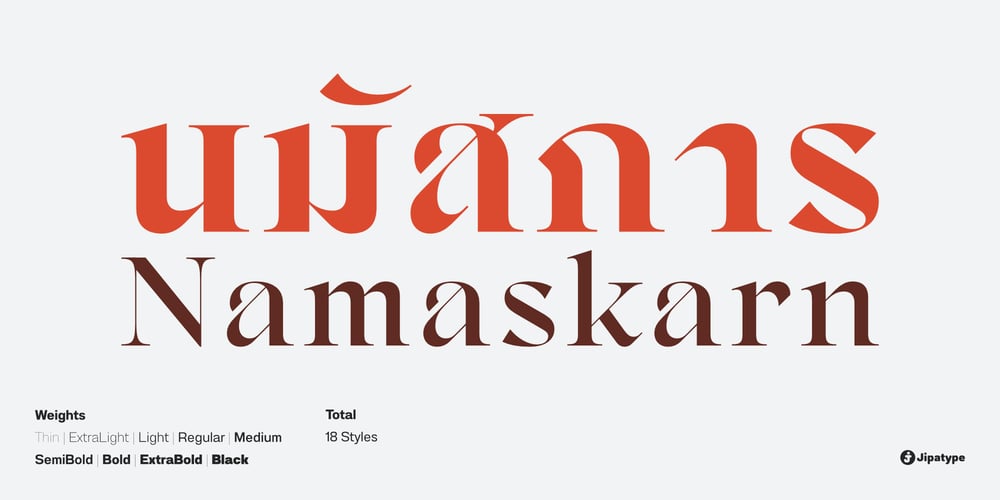
Namaskarn Font Family was designed by Anupap Jaichumnan and published by Jipatype. Namaskarn contains 18 styles and family package options. ฟอนต์ นมัสการ แบบอักษรได้แรงบันดาลใจจากเขียนตัวอักษรวิจิตรด้วยปากกาหัวตัด ที่มีองศาในการเดินเส้นที่ 45 องศา เลยเอาตัวเลข 45 องศามาใข้ในการออกแบบ สังเกตได้จากการจบเส้น เช่น “r” ปลายตัดที่ 45 องศา แบบอักษรมีความเปรียบต่างสูง เหมาะกับการใช้เป็นผาดหัว ข้อความสั่นๆ หรือ Quote มี 9 น้ำหนัก ทั้งตัวตรงและตัวเอียงรวมเป็น 18 สไตล์–Namaskarn Font inspired by flat calligraphy pen, with at 45 degrees when holding the pen, so the number 45 degrees was used in the design for example “r” at the terminal cut at 45 degrees. The font has a high contrast. Suitable for use as a headline, sub-headline or quote, comes in 9 weights, upright and italic for a total of 18 styles.